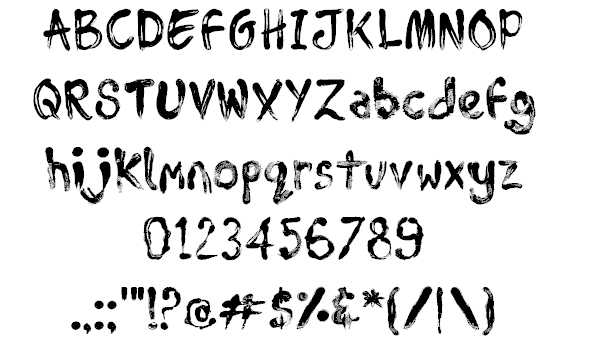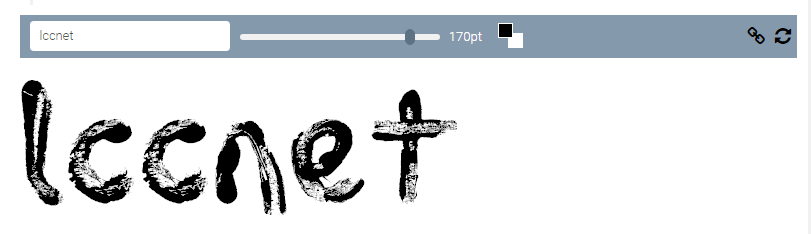
菜鳥救星分享:免費字體下載-Tajamuka Script font 發佈日期: 2021-03-032021-03-03 作者: Natty 文、菜鳥編 這次介紹的字體,也是一款手寫字體,根據開發的作者所述,字體的靈感來源是一場起義。但小編個人覺得有點水彩的樣式,字體中縫隙的呈現,就像使用水彩筆塗寫時,不規則的顏色散佈一樣。喜歡的不妨收藏起來吧。 字體名稱:Tajamuka Script font下載位置:http://bit.ly/2GTP4mr 網頁上方的縮圖可以找到全部字母的呈現。 授權使用也可免費使用在商業用途上。 下方的預覽視窗也可先將文字填入看效果,滿意再下載。 字體的下載量與收藏也都有不錯的表現。 將檔案下載好解壓縮,內容包含一個說明檔案與字體檔。 安裝字體。 免費字體為網路搜尋而來,使用權限請以官方文件與說明為主 加入菜鳥救星官方Line並回覆「我想看文章」,不定期獲得更多知識吧! 不同頻道,不同知識! Facebook Instagram Youtube 分享此文: 分享到 X(在新視窗中開啟) X 分享到 Facebook(在新視窗中開啟) Facebook 分享到 Telegram(在新視窗中開啟) Telegram 以電子郵件將連結傳送給朋友(在新視窗中開啟) 電子郵件 請按讚:喜歡 正在載入... 相關